Как проверить стыки букв рукописного шрифта на печатной пробе
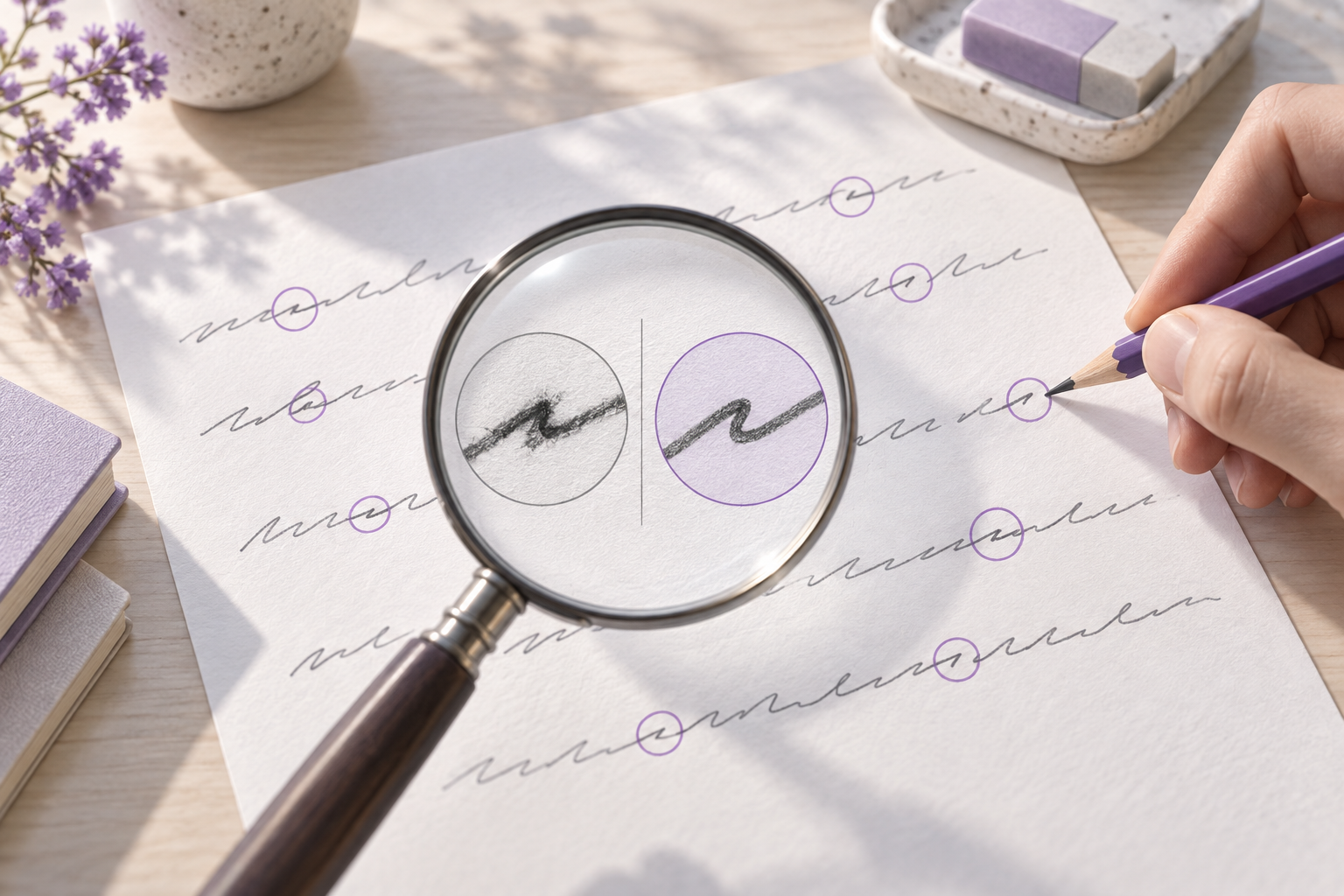
Стыки букв в рукописном шрифте проверяют не по одной паре на экране, а в коротком наборе слов и фраз, напечатанных в предполагаемом размере. Такая проба показывает, где соседние знаки визуально слипаются, распадаются или меняют ритм. Ниже — способ составить контрольный текст, разметить наблюдения и отличить проблему конкретной пары от ошибки всего набора или печати.
Что именно считать проблемой стыка
Стык — это участок между соседними глифами, где формы встречаются или воспринимаются как единое движение. В связном почерке штрихи могут физически не касаться, но глаз всё равно соединит их в одну линию; бывает и наоборот: соприкосновение допустимо, если траектория остаётся понятной. Поэтому цель проверки — не механически раздвинуть все пары, а сохранить ясность слова и общий ритм.
Разделяйте три разных симптома. Слишком тесная пара превращается в тёмный узел или ложную лигатуру. Слишком большая дистанция прерывает движение и выглядит как пробел внутри слова. Наконец, неровность может возникать не между конкретными формами, а из-за чередования широких и узких букв: отдельные стыки чистые, но слово «пульсирует». Для каждого симптома нужна своя проверка и своя правка.
Не оценивайте только линию соединения. Смотрите на просветы вокруг неё, на наклон, на высоту входного и выходного штриха, а также на то, где глаз начинает различать следующую букву. Если участок читается только потому, что вы уже знаете слово, такой пример полезно отметить для дополнительной проверки, но не считать сразу ошибкой шрифта: контекст способен подсказать чтение.
Сначала составьте карту рискованных переходов
Обычный связный абзац редко содержит все пары, которые стоит проверить. Перед набором пробы запишите признаки форм, а не только список букв: закрытый овал, высокий восходящий штрих, нижний выносной элемент, острый вход, короткий выход, петля, резкая смена направления. Затем отметьте переходы, где два признака соседствуют и могут конкурировать за одно пространство.
Например, у пары «лк» выход первой буквы может подойти к восходящему штриху следующей; в «по» округлая форма может сжать промежуток после прямого входа; в слове «шишка» повторяются близкие по рисунку элементы, и проявится усталость ритма. Это не готовые универсальные диагнозы, а примеры того, какие отношения стоит искать именно в вашем почерке. Если у конкретной формы нет петли или выносного элемента, не включайте её в перечень только потому, что такая пара встречается в чужой гарнитуре.
Соберите матрицу из нескольких групп: прямой штрих рядом с дугой, две дуги, острый выход перед высоким штрихом, короткая форма перед широкой, повтор одинаковых знаков и переход с нижним выносным элементом. Для каждой группы выберите два-три реальных слова. В коротких словах легко заметить дефект пары; в длинных — проверить, не накапливается ли неудобство к середине строки.
Старайтесь использовать реальные слова, которые читатель узнаёт без подписи. Бессмысленная последовательность из букв полезна на этапе построения глифов, но на печатной пробе она заставляет угадывать и повышает роль подсказки. Если нужная комбинация редко встречается, вставьте её в имя, термин или нейтральную фразу и пометьте, почему этот фрагмент выбран. Не превращайте пробу в скороговорку: естественная лексика помогает увидеть, как человек читает, а не только как рассматривает формы.
Как собрать контрольный текст без повторов ради повторов
Начните с таблицы: переход, слово, ожидаемый риск, место на листе, результат. В колонке «переход» укажите пару глифов; в «ожидаемом риске» — возможный симптом, например слипание выхода с овалом. Эта запись не предрешает результат. Она помогает проверить гипотезу и после печати не переименовать любой заметный участок в то, чего вы ожидали.
Включите короткий блок из слов, подобранных для отдельных пар, затем связную фразу и небольшой абзац. Короткий блок показывает локальное поведение без долгого поиска нужного места. Фраза проверяет стыки в естественном чтении, а абзац показывает, как они работают среди повторов, пробелов и соседних строк. Контрольные примеры ставьте рядом с нейтральным текстом, чтобы можно было сравнить их плотность и не судить только по специально подобранным «сложным» словам.
Полезно повторить часть слов в двух контекстах: отдельно и внутри фразы. Если слово выглядит хорошо само по себе, но теряется в строке, причина может быть в соседних словах, интервалах между словами или выключке, а не в его внутренних стыках. Для этого сохраняйте одинаковыми кегль, гарнитуру, межстрочный интервал и параметры печати. Иначе вы сравните разные условия.
Не нужно бесконечно дублировать одну пару. Повтор помогает проверить устойчивость впечатления, но десятки одинаковых слов заставляют замечать именно этот дефект и быстро утомляют читателя. Достаточно нескольких независимых слов и одного фрагмента, где переход встречается в естественном окружении. Если вариантов слова нет, добавьте контроль с соседней по рисунку парой: так станет понятнее, является ли проблема частной или повторяется у общего типа формы.
Контрольная проба стыков должна проверять конкретные отношения между формами, но оставаться похожей на обычное чтение. Карта переходов, подбор реальных слов, печать в целевом размере и журнал точечных правок превращают субъективное «тут тесно» в задачу, которую можно повторить. Когда набор работает на бумаге, создайте или доработайте его в Fontgenerator и сохраните проверенную версию.